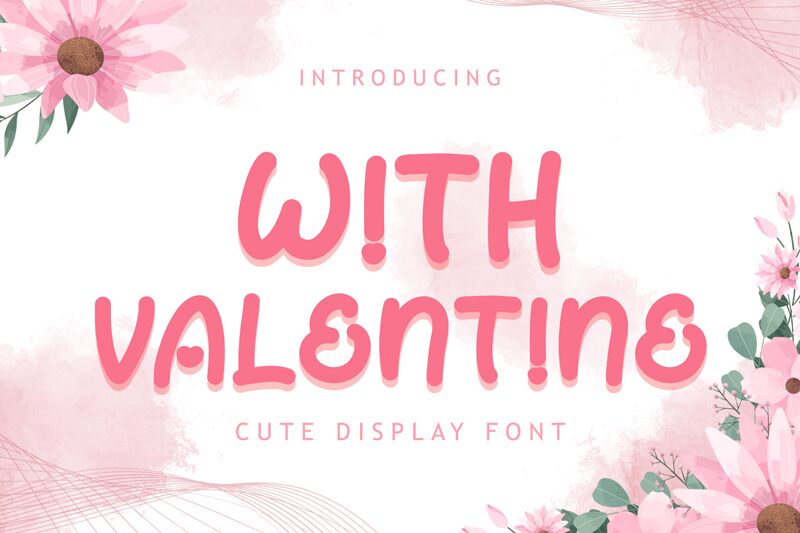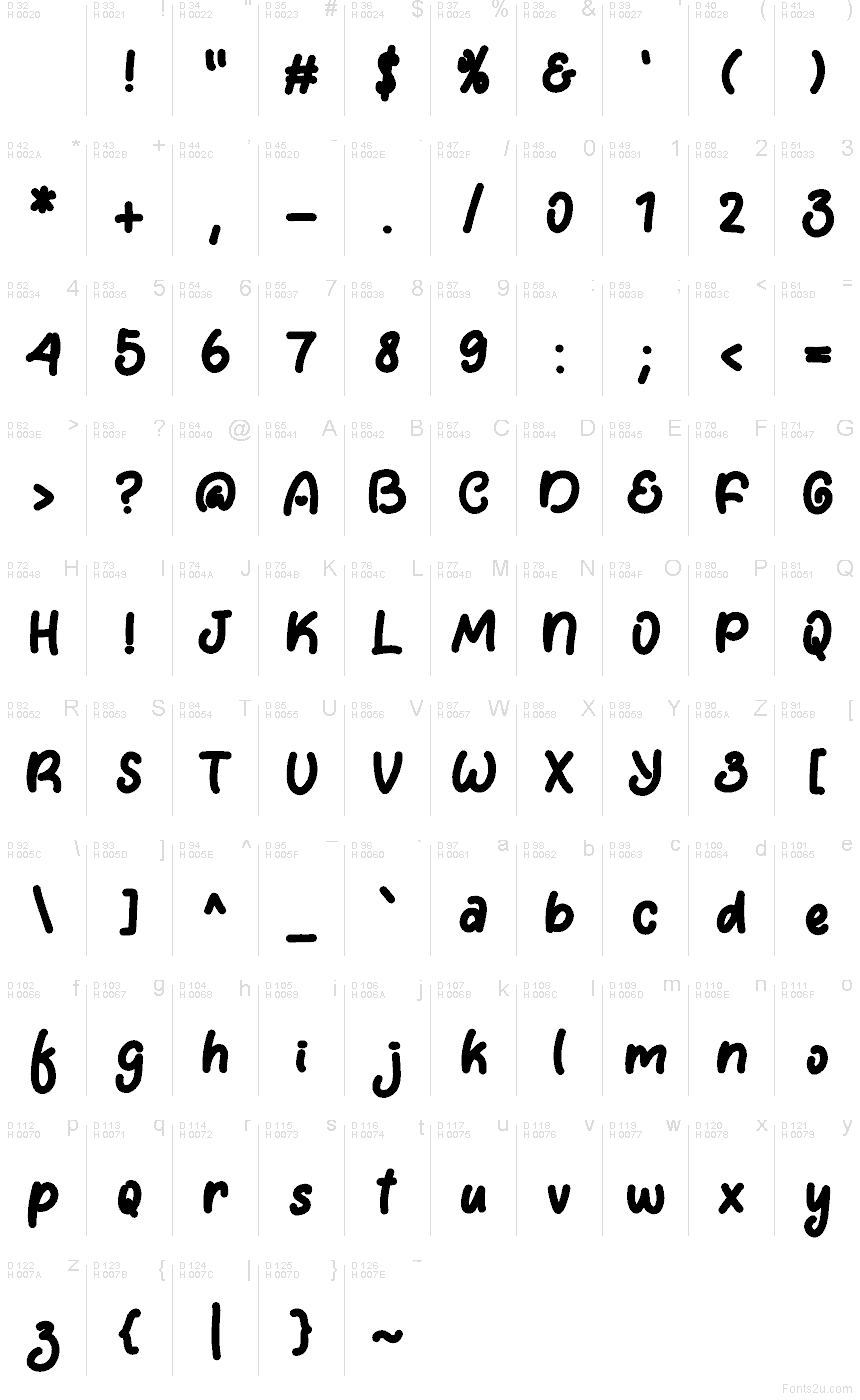
With Valentine
With Valentine ist eine kostenlose Comic-Display-Schrift mit abgerundeten, handgeschriebenen Formen und fließenden, geschwungenen Kurven. Die Buchstaben wirken locker und lebendig, was der Schrift einen freundlichen, ungezwungenen Charakter verleiht, ohne unordentlich zu wirken.
With Valentine eignet sich hervorragend für Grußkarten, Einladungen, Social-Media-Grafiken, Plakat-Überschriften und fröhliche Zitat-Designs, da die weichen Formen persönlich und leichtfüßig wirken. Diese kostenlose Schriftart passt zudem wunderbar zu Geburtstags-Headlines, Bastelprojekten für Kinder und kurzen Marken-Slogans, bei denen ein handgeschriebener Stil mit einer warmen, sympathischen Note gefragt ist.